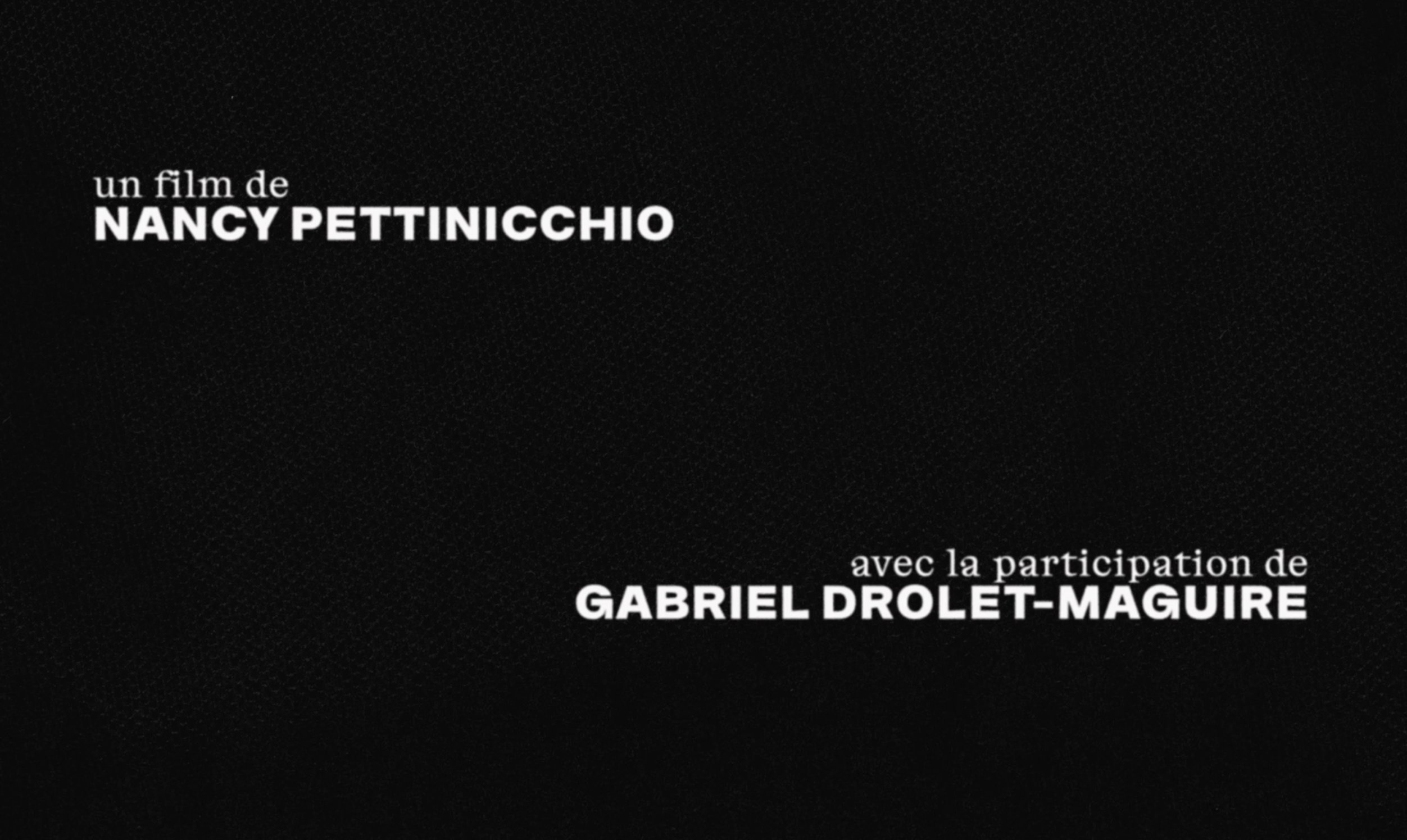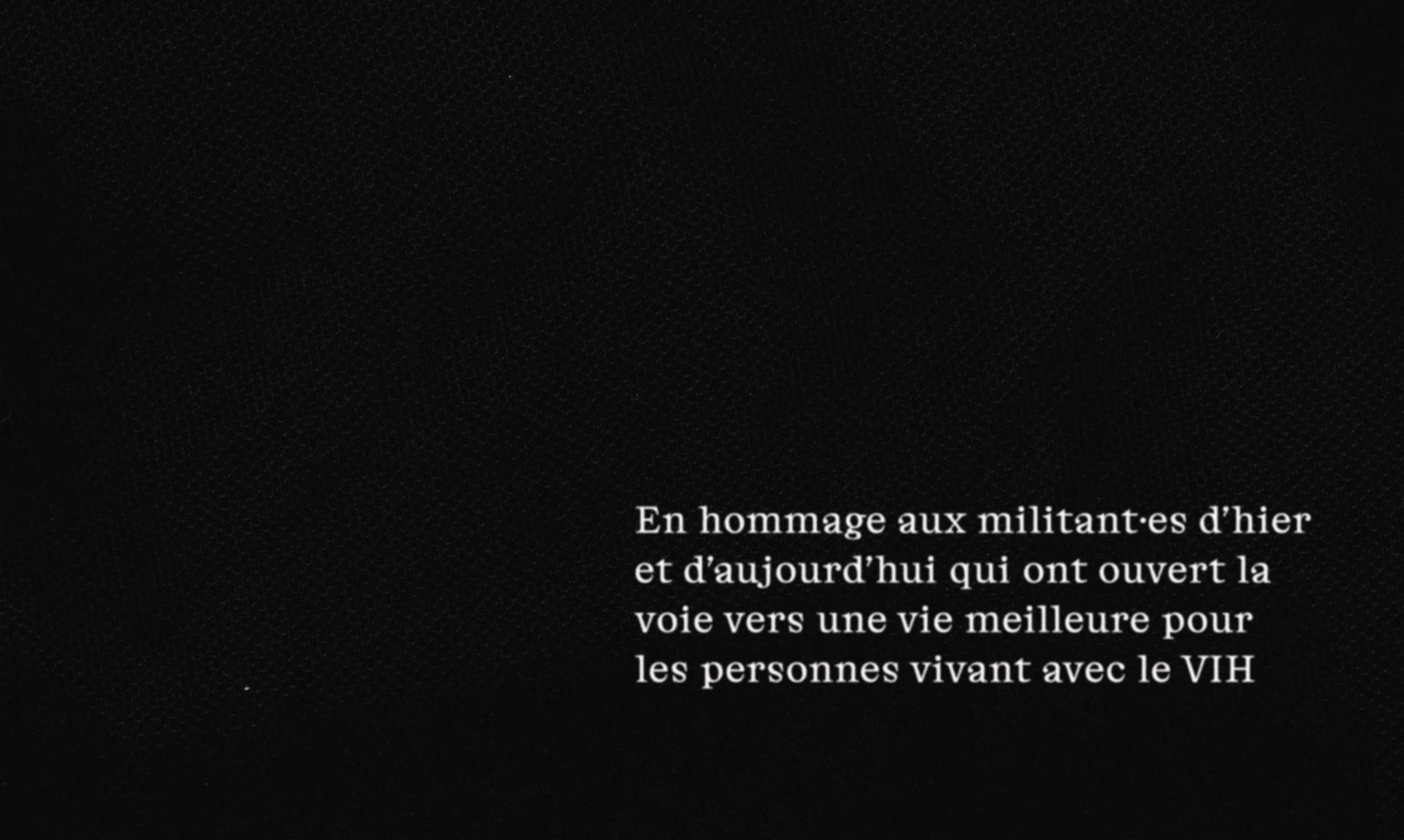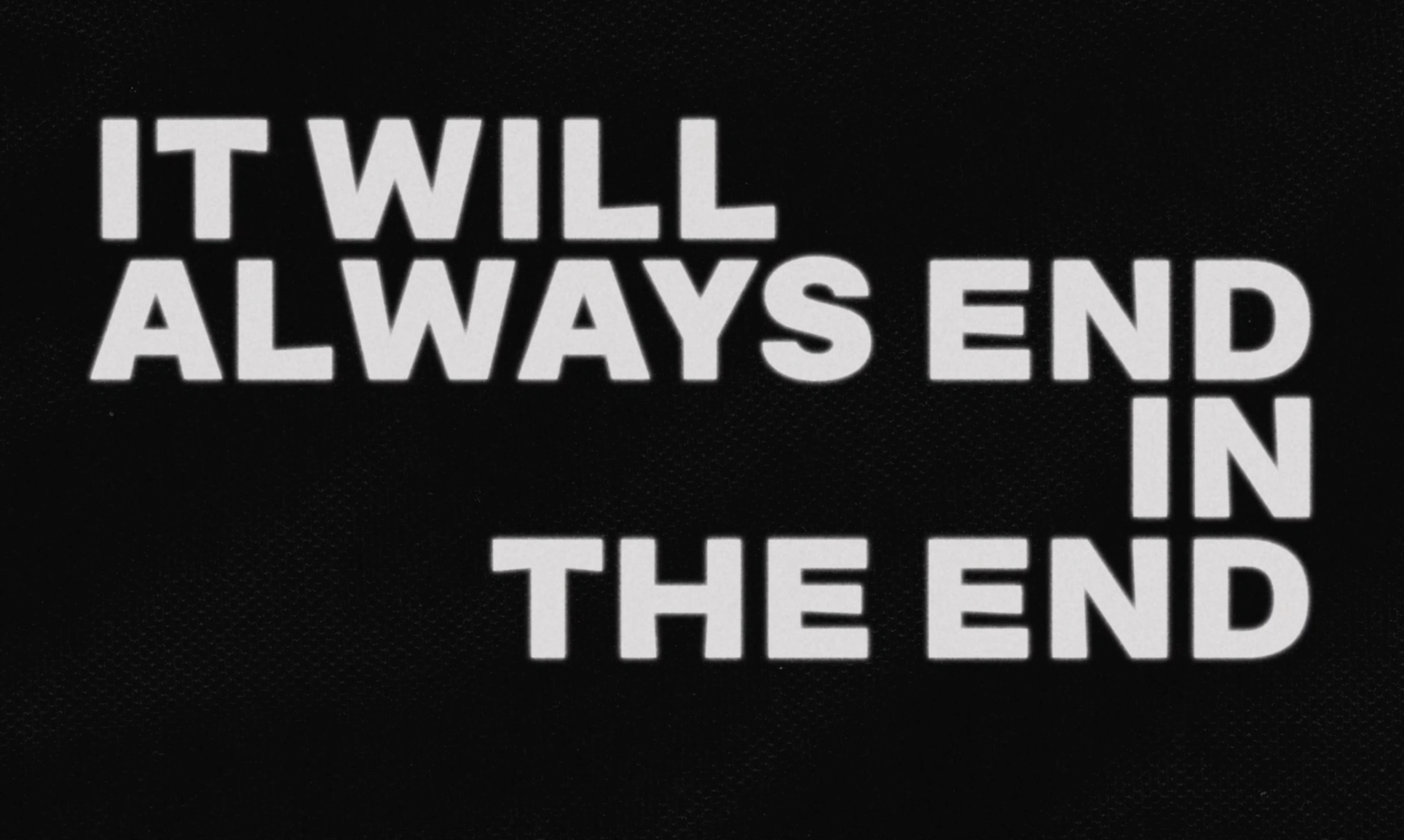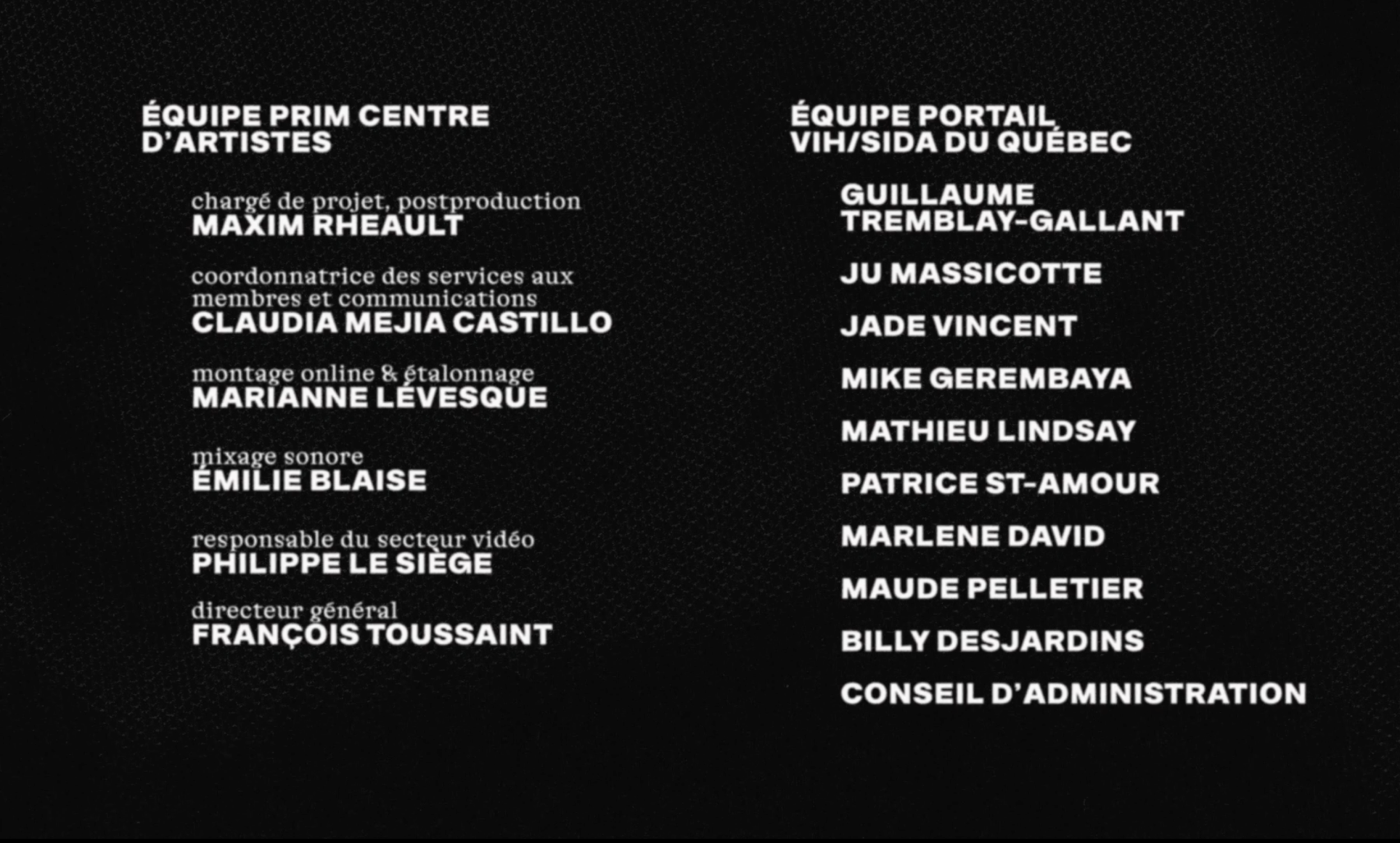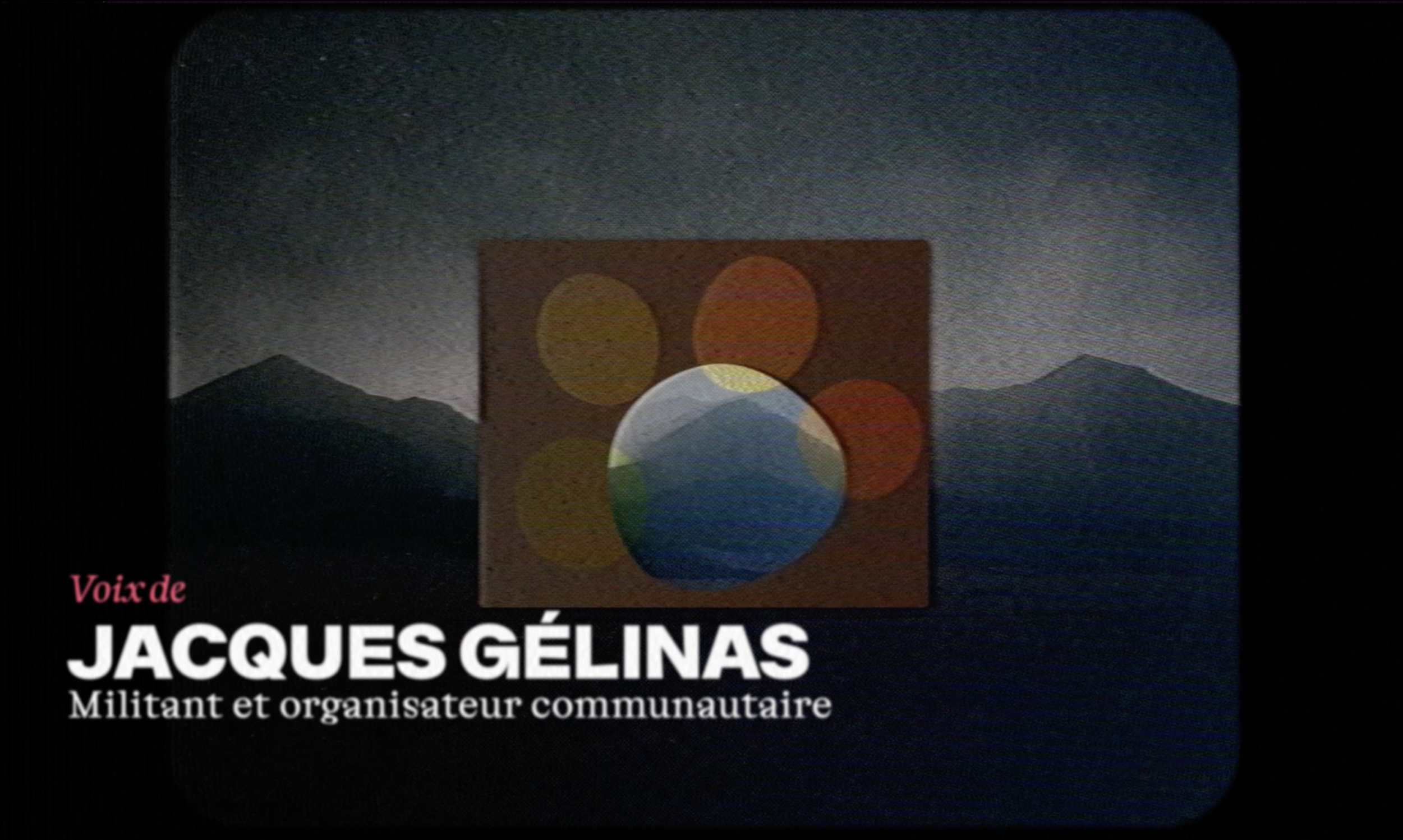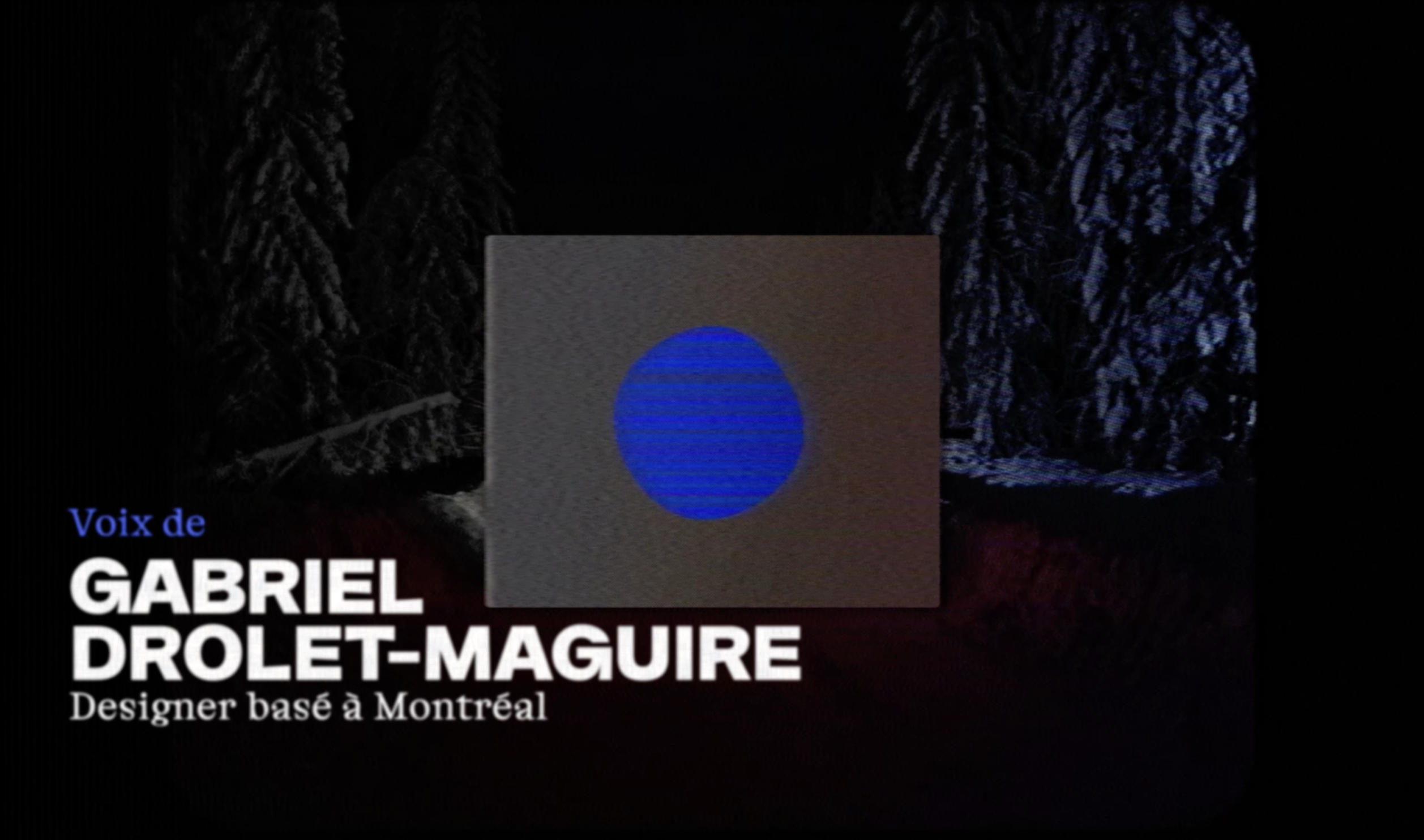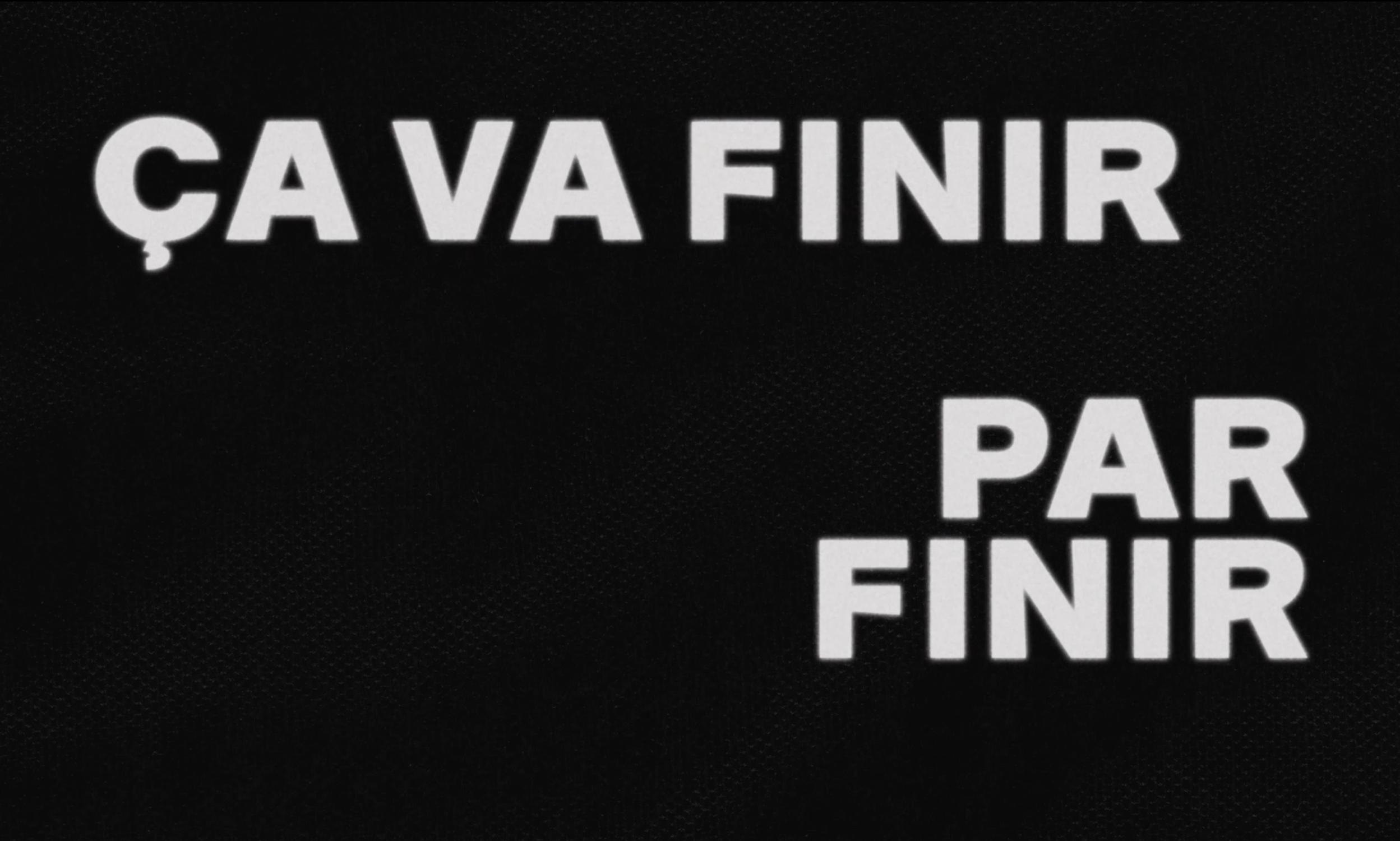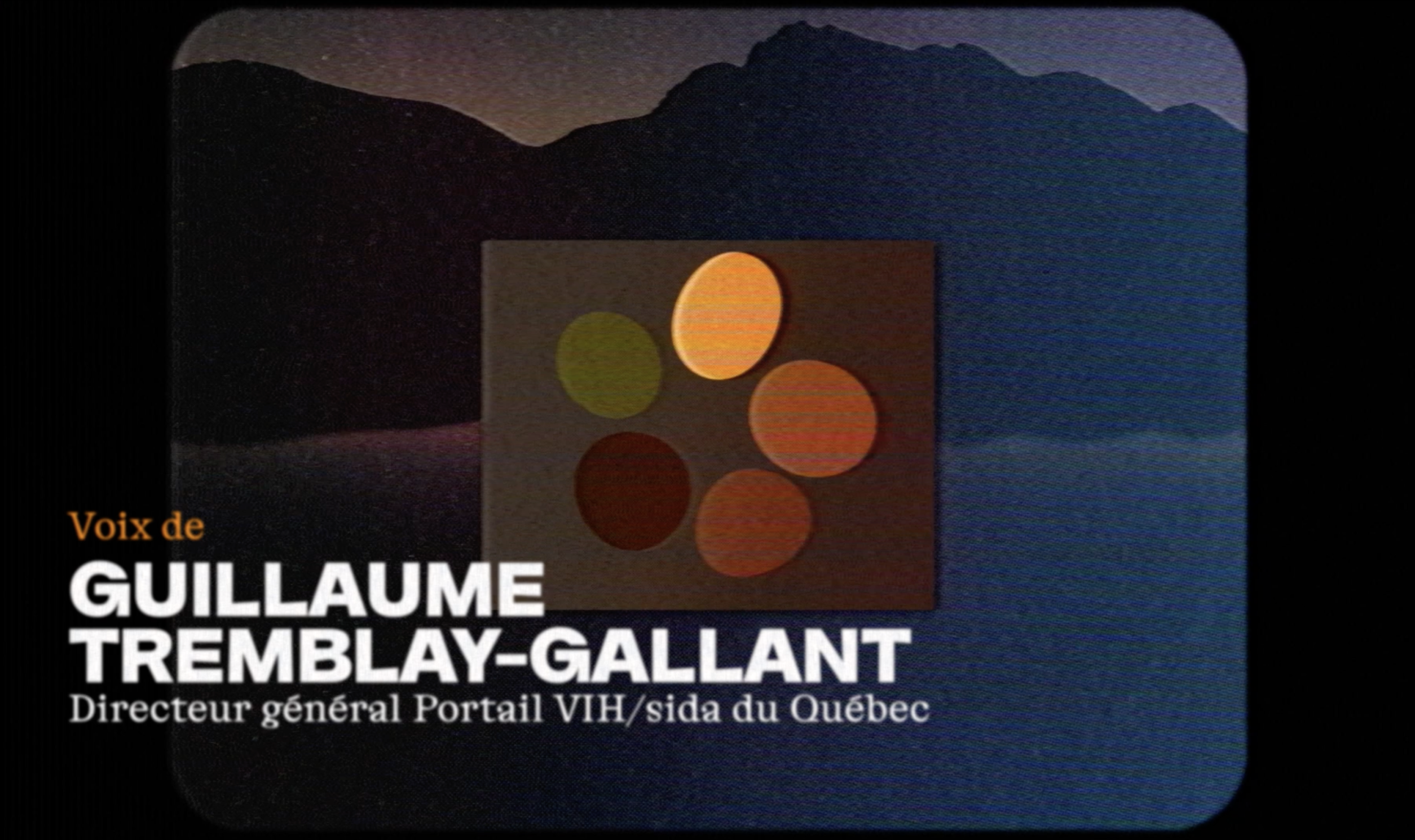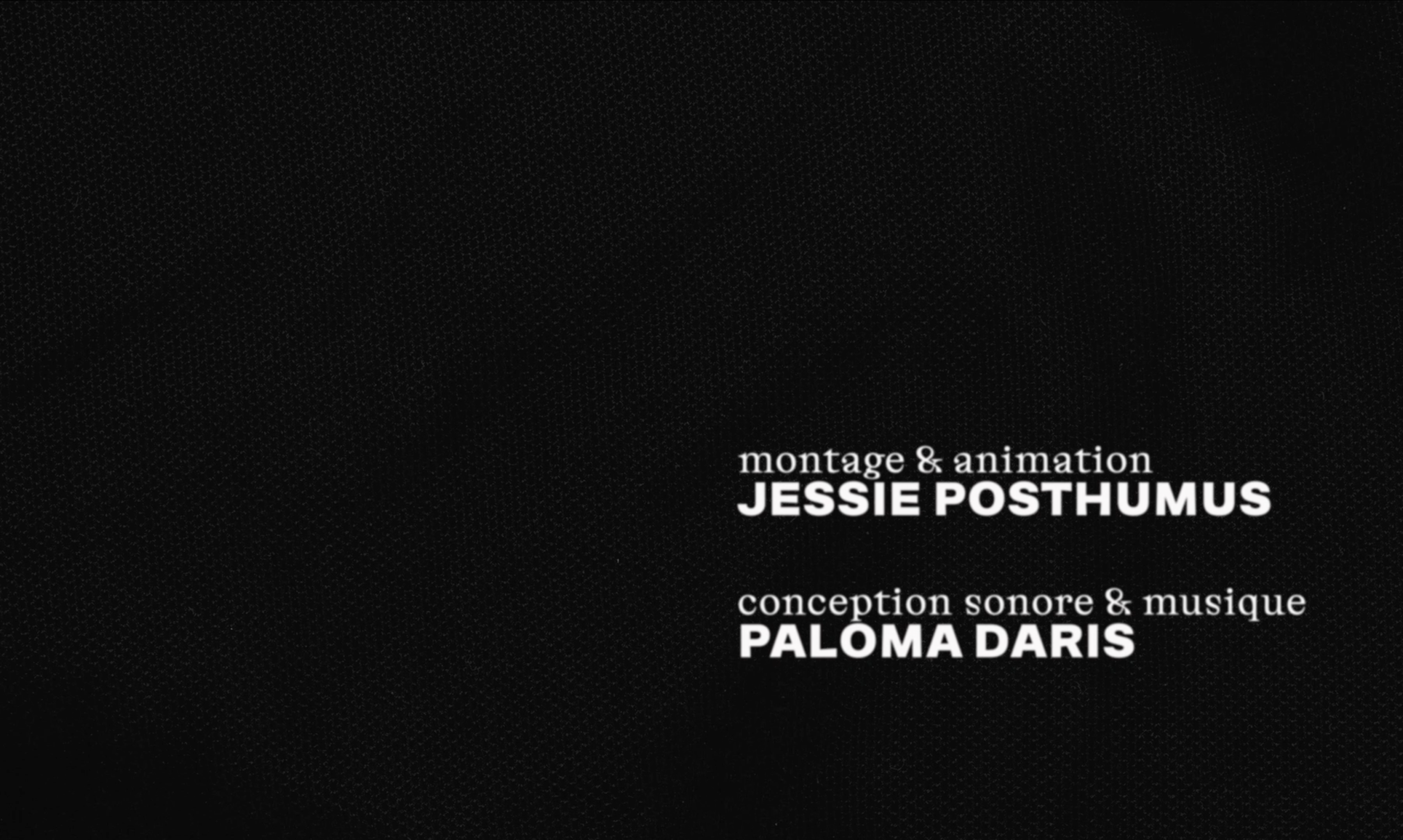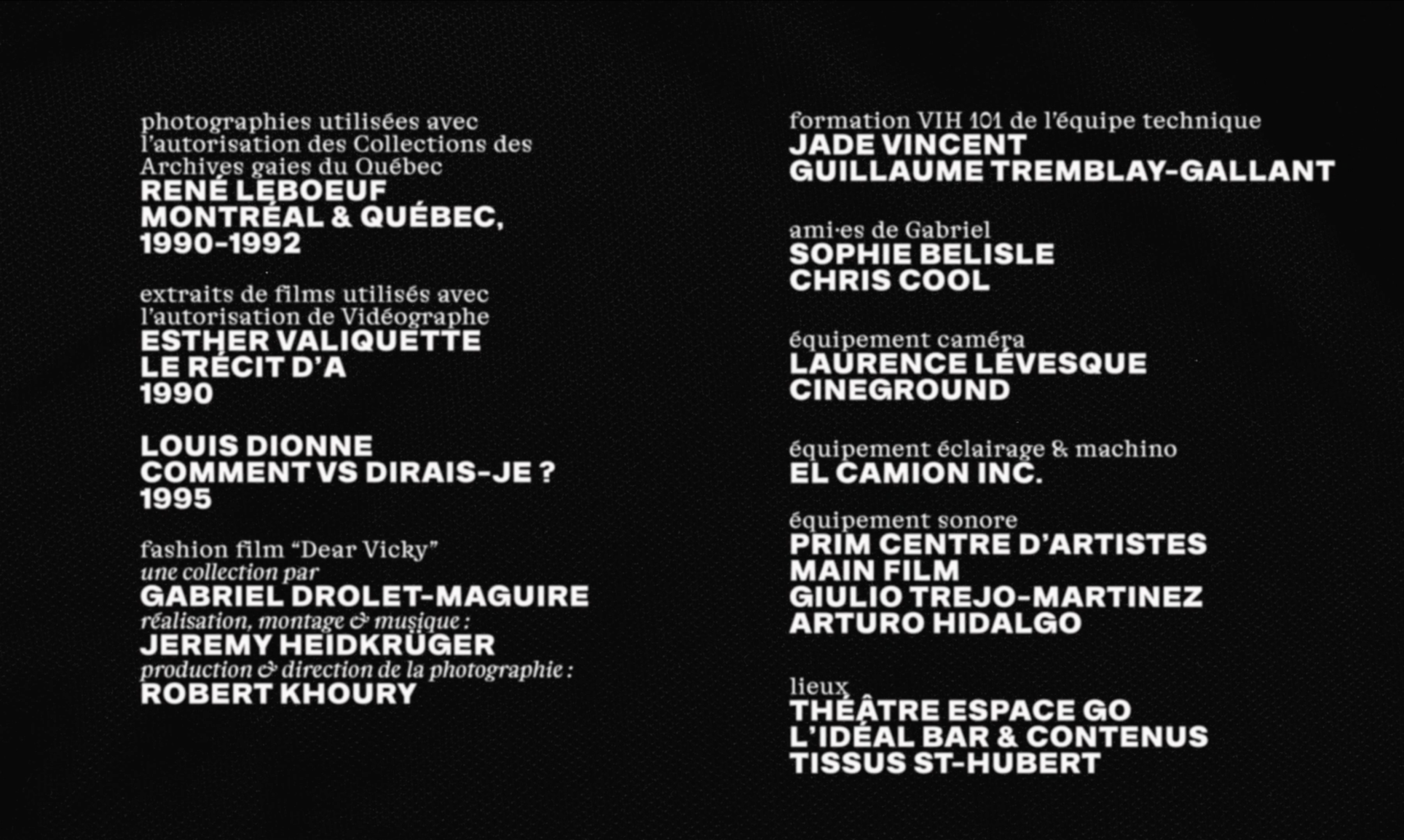
Ça Va Finir Par Finir ist ein Kurzfilm von Nancy Pettinicchio. Er wurde in Zusammenarbeit mit dem Portail VIH/sida du Québec produziert und untersucht das Kunstschaffen als eine wesentliche Form des HIV/AIDS-Aktivismus.
Die Titelgestaltung verbindet eine fette Grotesk mit einer eigenwilligen Serifen-betonten Schrift und verweist so zum einen auf HIV/AIDS-Aktivismus-Poster aus den 80er und 90er Jahren und stellt zum anderen einen Kontrast dar zwischen Strenge und Zärtlichkeit. Die im Hintergrund sich wechslenden Bilder von Stoffen sprechen von dem Schaffen des Protagonisten als Modedesigner und der starke Korn und Haptik fügen sich in die kollagenhafte Form des Filmes ein.
Schrift: Bastardo Grotesk von Giulia Boggio & Nordic Pavillion von Scott Van der Zee